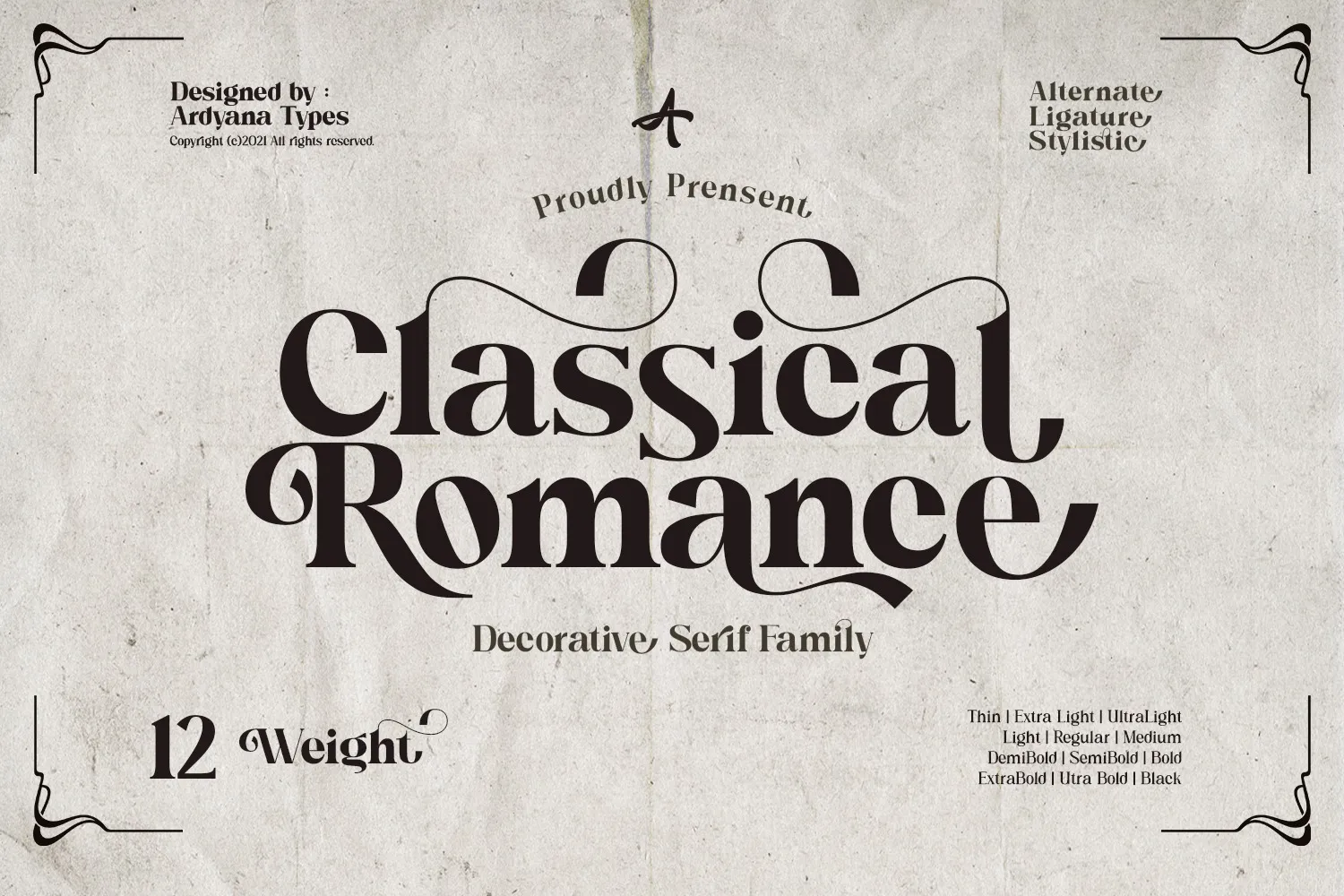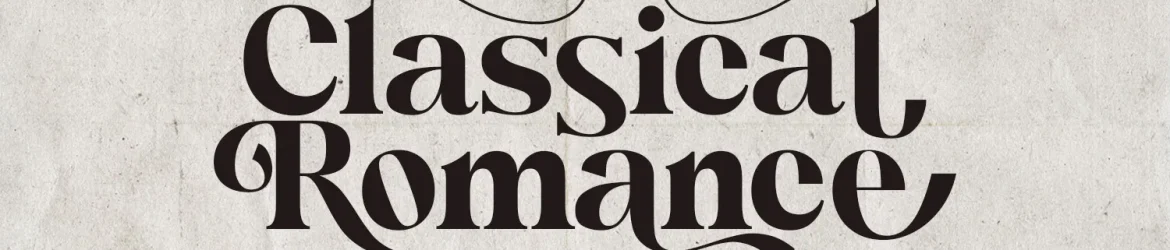
Ardyanatypes criou a “Classical Romance Font”, uma serif única que traz 125 alternativas para revigorar qualquer projeto gráfico que você ame. Este tipo estável e versátil se destaca por sua superfície levemente rústica, complementando perfeitamente os detalhes suaves e convencionais do ‘Classical Romance’. Esta fonte exibicionista tem o poder para transformar logos e marcas de acordo com suas necessidades, bem como headlines, etiquetas de embalagens, panfletos, revistas online, veículos automotivos e muito mais. Seja você um designer ou criador gráfico, a ‘Classical Romance Font’ é uma escolha inteligente para estilizar seus projetos com elegância sofisticada.